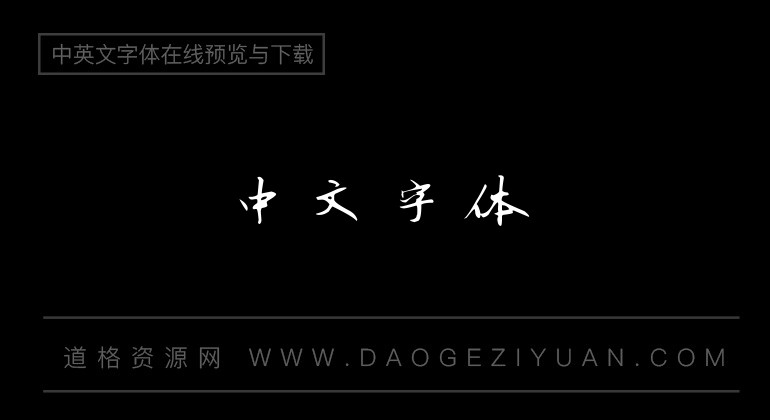
书体坊王学勤钢笔行书
书体坊王学勤钢笔行书是一种独特的字体,它是由王学勤先生所创作的。这种字体的特点是字母笔画粗细均衡,笔画细腻,极具灵动性,让人感到非常舒服。书体坊王学勤钢笔行书字体的字母形状非常精美,且具有很强的表达力,可以用来表达深刻的思想。它可以用来书写书信、文章等,也可以用来制作名片、海报等。
书体坊王学勤钢笔行书是一款非常不错的手写艺术字体,具有很好的视觉感,适合于文化类的宣传设计、商业类品牌的广告和产品包装设计以及个性化文字排版等较多场景。